Македонская «ѕ» в шрифте: как проверить форму, код и различимость
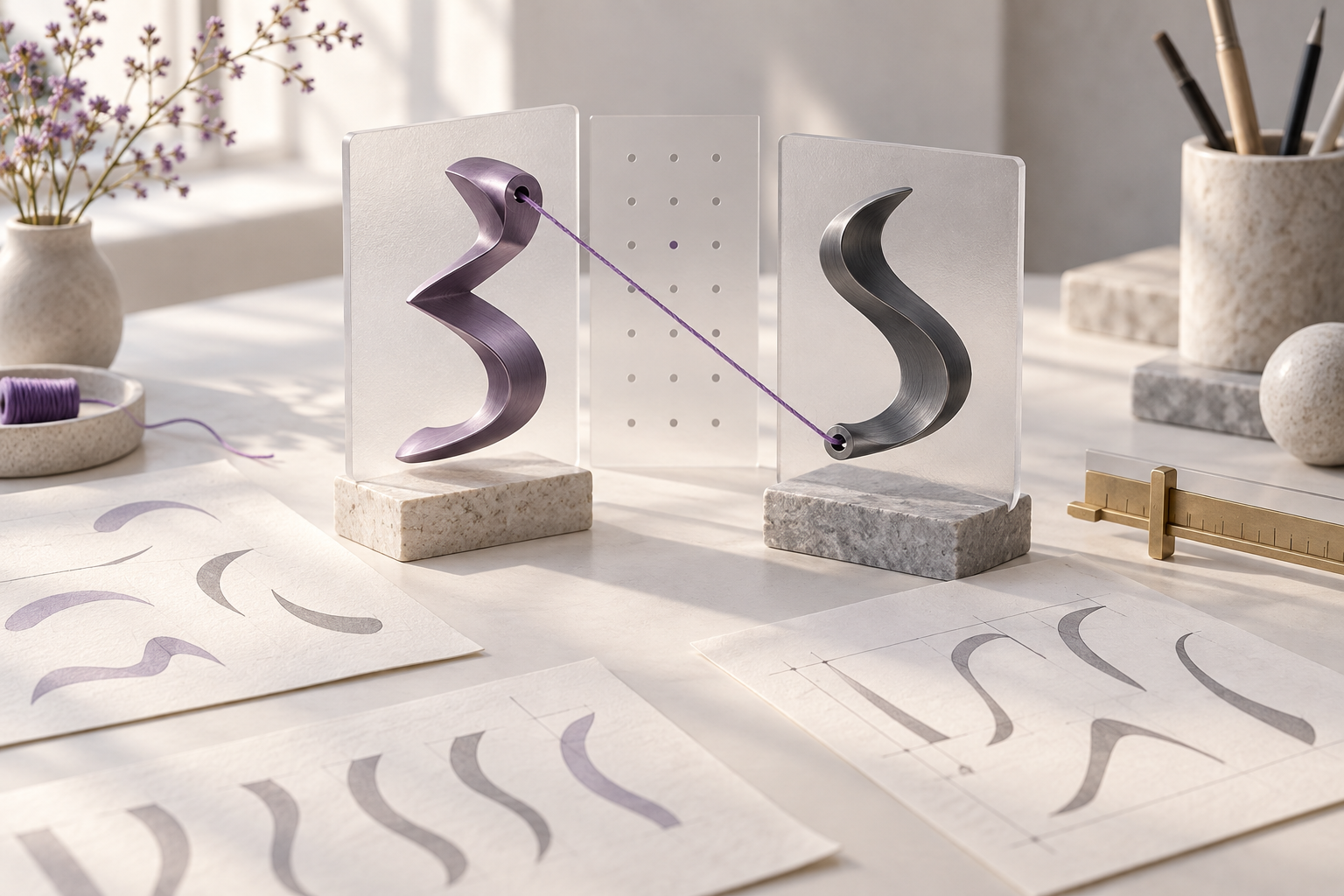
Кириллическая «ѕ» — отдельная буква македонского алфавита, хотя её строчная форма во многих гарнитурах почти не отличается от латинской s. При разработке шрифта важно сохранить не только узнаваемый рисунок, но и отдельную Unicode-идентичность, корректную пару регистра и предсказуемый набор в македонском тексте. Ниже — практический маршрут от эскиза до проверки файла.
Что именно проверять в букве «ѕ»
У македонской буквы есть прописная «Ѕ» и строчная «ѕ». В таблице Unicode это CYRILLIC CAPITAL LETTER DZE U+0405 и CYRILLIC SMALL LETTER DZE U+0455. Это не латинские S и s: у них другие кодовые точки — U+0053 и U+0073. Базовые сведения можно сверить в официальной таблице Unicode для кириллицы.
Для читателя строчная форма может выглядеть как обычная латинская s, и сама по себе такая похожесть не означает ошибку. Ошибка возникает, если в текст вместо ѕ попала латинская буква, шрифт не содержит нужный символ, прописная и строчная формы построены несогласованно или при экспорте перепутались кодовые точки. Внешняя картинка не показывает, какой именно символ набран.
Буква нужна не только как редкий тестовый знак: официальный македонский цифровой толковый словарь включает её в показ алфавита, а статья «ѕвезда» даёт материал для проверки в слове и в строке. Поэтому проекту с македонским текстом важно тестировать её наравне с базовыми кириллическими буквами.
Сначала определите, нужен ли знак проекту
Перед рисованием решите, какие языки должен поддерживать шрифт. Если задача ограничена русским алфавитом, добавлять каждую дополнительную кириллическую букву «на всякий случай» необязательно. Если шрифт заявлен для македонского, ожидается осмысленная поддержка всего нужного набора, а не только символов, общих с русским.
Зафиксируйте требования в коротком списке: македонский текст будет набирать сам пользователь или его вводят из внешнего источника; нужны ли прописные и строчные буквы; будет ли набор использоваться в заголовках, длинном тексте или интерфейсных подписях; какие форматы файла и приложения входят в проверку. Эти ответы определяют, насколько внимательно нужно смотреть на набор, насыщенность, курсив и экспорт.
Не делайте вывод о поддержке языка только по надписи «кириллица» в описании гарнитуры. Такое слово может означать лишь базовый русский набор. Сверьте таблицу символов конкретного файла или вставьте характерную македонскую строку в приложение, где будет работать шрифт. Для рукописного проекта особенно полезно записать нужный символ в шаблон вместе с остальным алфавитом: тогда его можно нарисовать в той же манере, а не пристроить к готовой системе случайным образом.
Как построить прописную и строчную формы
Начните с места буквы в общей конструкции шрифта. «Ѕ» и «ѕ» должны выглядеть родственными по пластике, контрасту и характеру окончания штриха. При этом регистры не обязаны быть простыми копиями друг друга. Сравните высоту прописных и строчных, ширину знаков, положение относительно базовой линии и общий ритм с соседними буквами набора.
Если гарнитура построена на спокойных округлых формах, не превращайте знак в демонстративную эмблему. Если почерк угловатый или наклонный, повторите в нём тот же угол и логику нажима. Сравнение со S и s полезно как проверка силуэта, но не как требование скопировать латинский знак без адаптации. Решение должно работать внутри кириллической системы: рядом с «З», «С», «Е» и другими буквами, с которыми пользователь видит его в настоящих словах.
Прописная не должна быть забытым дублем
Отдельно нарисуйте «Ѕ» и проверьте её в слове с прописной первой буквой, например в начале тестовой строки «Ѕвезда». Не полагайтесь только на автоматическое увеличение строчной «ѕ». Сравните ширину и визуальный вес прописных с остальными заглавными, проверьте расстояние до следующей буквы, а затем поставьте знак в коротком заголовке.
Учитывайте начертания, которые входят в состав проекта. Если есть курсив, он должен сохранять узнаваемую структуру и не превращаться в знак с другим характером. Для переменного шрифта проверяйте оси на крайних значениях: в самом светлом или сжатом варианте тонкие участки не должны исчезнуть, а в тяжёлом — просветы не должны закрыться.
Метрики: проверьте не одну букву, а её соседей
Даже если рисунок «ѕ» хорош сам по себе, неудачная ширина может сделать слово неровным. Начните с базовых метрик: высоты строчных и прописных, боковых полей, позиции на базовой линии. Затем проверьте пары, в которых у знака есть округлая или диагональная сторона. Оптическое расстояние оценивают глазами в контексте, а не только по числовым значениям полей.
Для начальной пробы возьмите слово «ѕвезда» из македонского словаря и варианты для разных регистров: «Ѕвезда», «ѕвезда», «ЅВЕЗДА». Посмотрите на набор в обычном тексте, заголовке и крупном масштабе. В отдельной диагностической строке поставьте рядом «ѕ», латинскую s, кириллическую «з» и «с». Такая строка показывает сходство и помогает заметить случайную подмену, но не заменяет проверку настоящего слова.